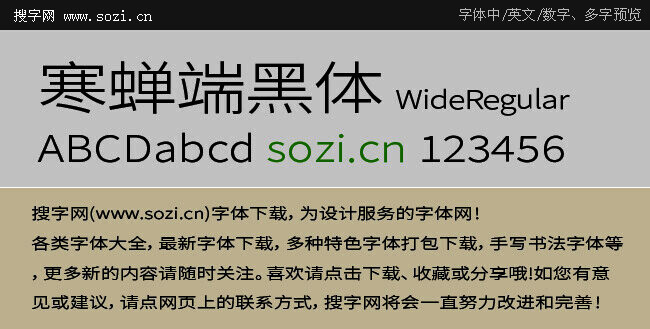
寒蟬端黑體WideRegular
搜字網(wǎng)給大家提供一款寒蟬端黑體WideRegular中文字體下載,寒蟬端黑體是基于思源黑體進行調(diào)整的黑體字體,在原字體風格上重新插值生成,Wide系列的寒蟬端黑體是思源黑體的寬體版本。適用于標題設計、海報設計、書籍排版以及網(wǎng)頁設計等應用。